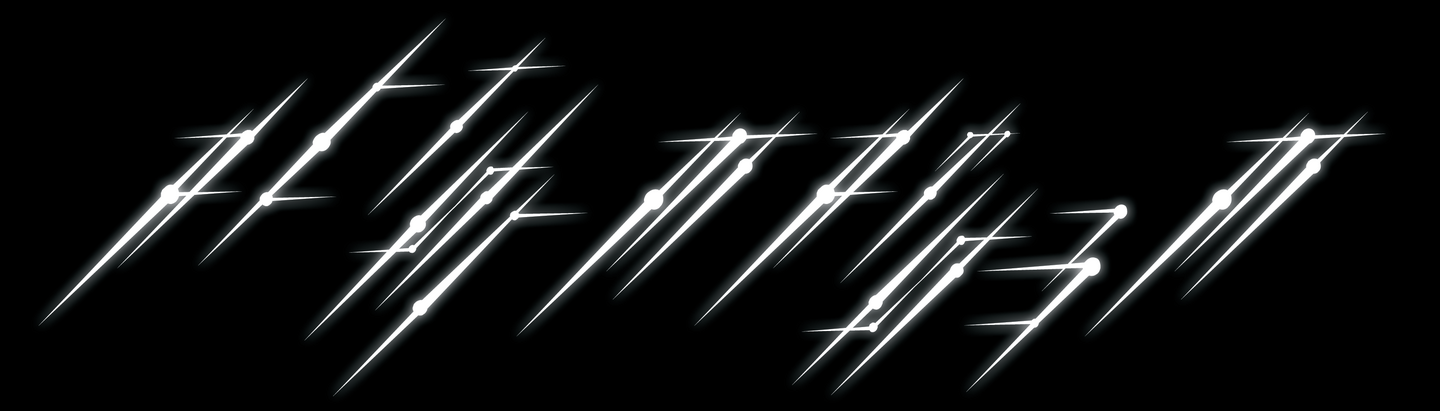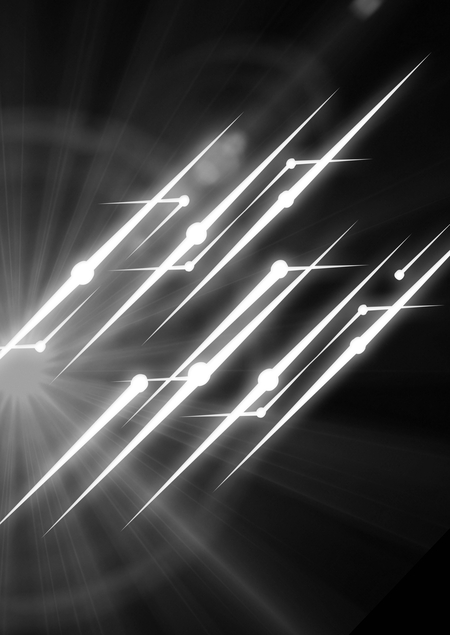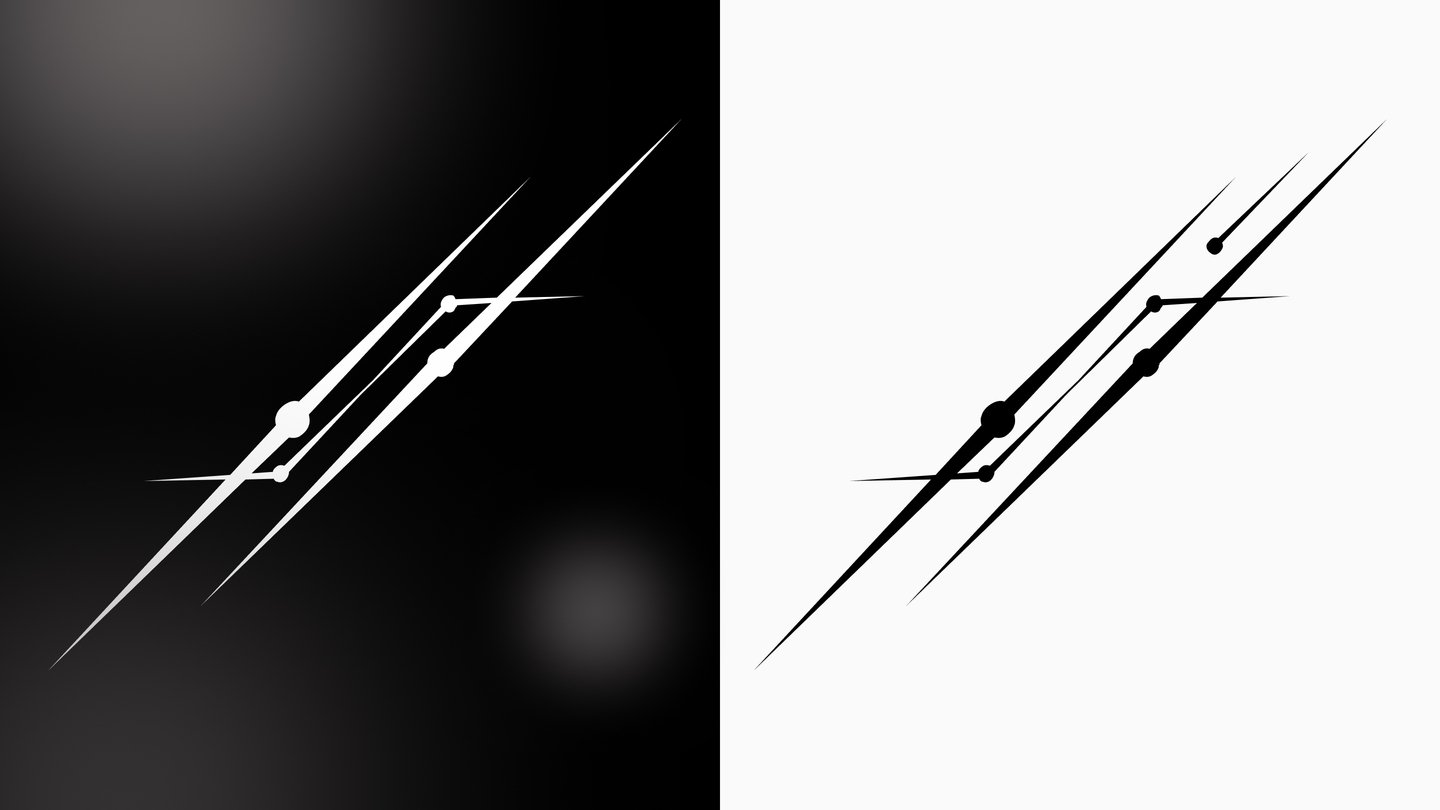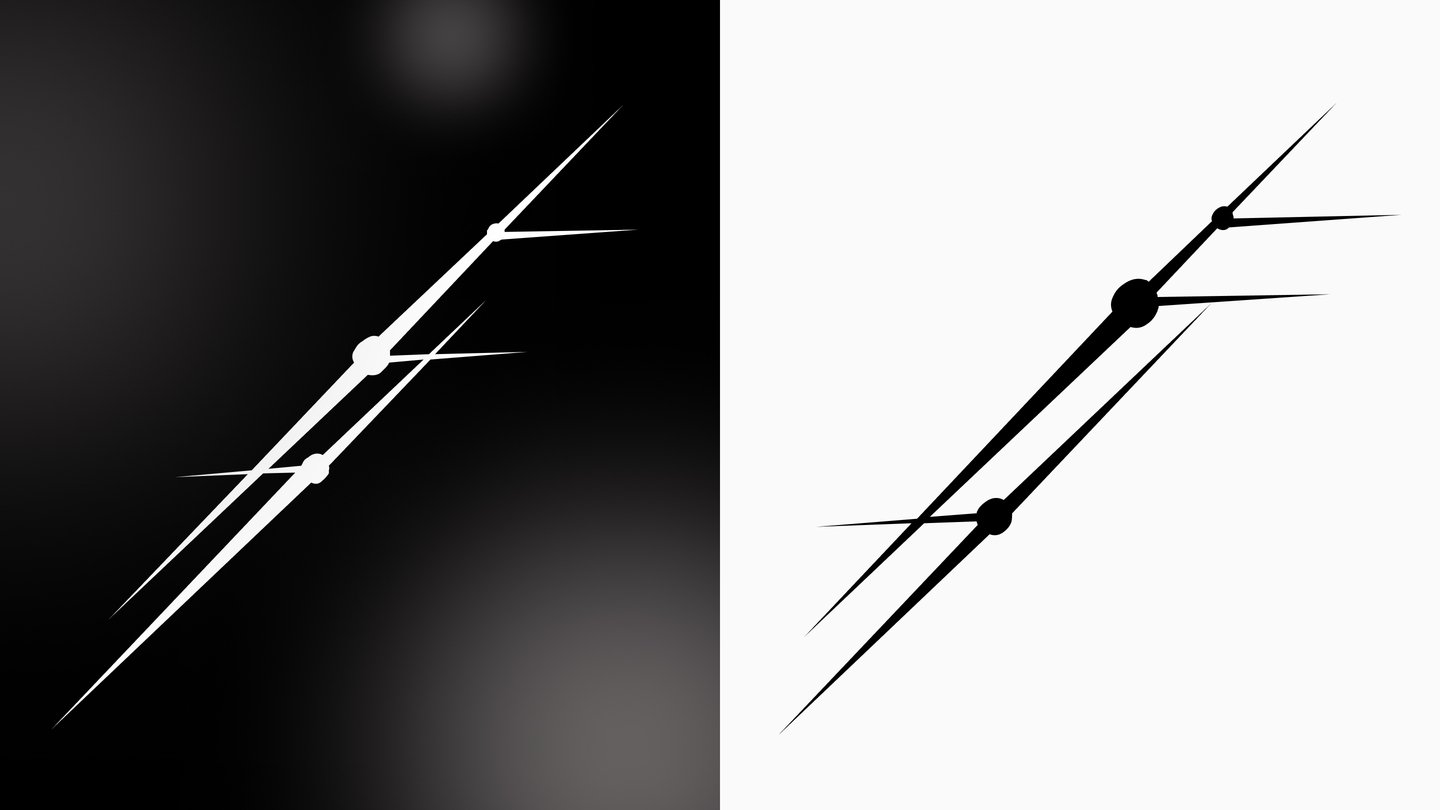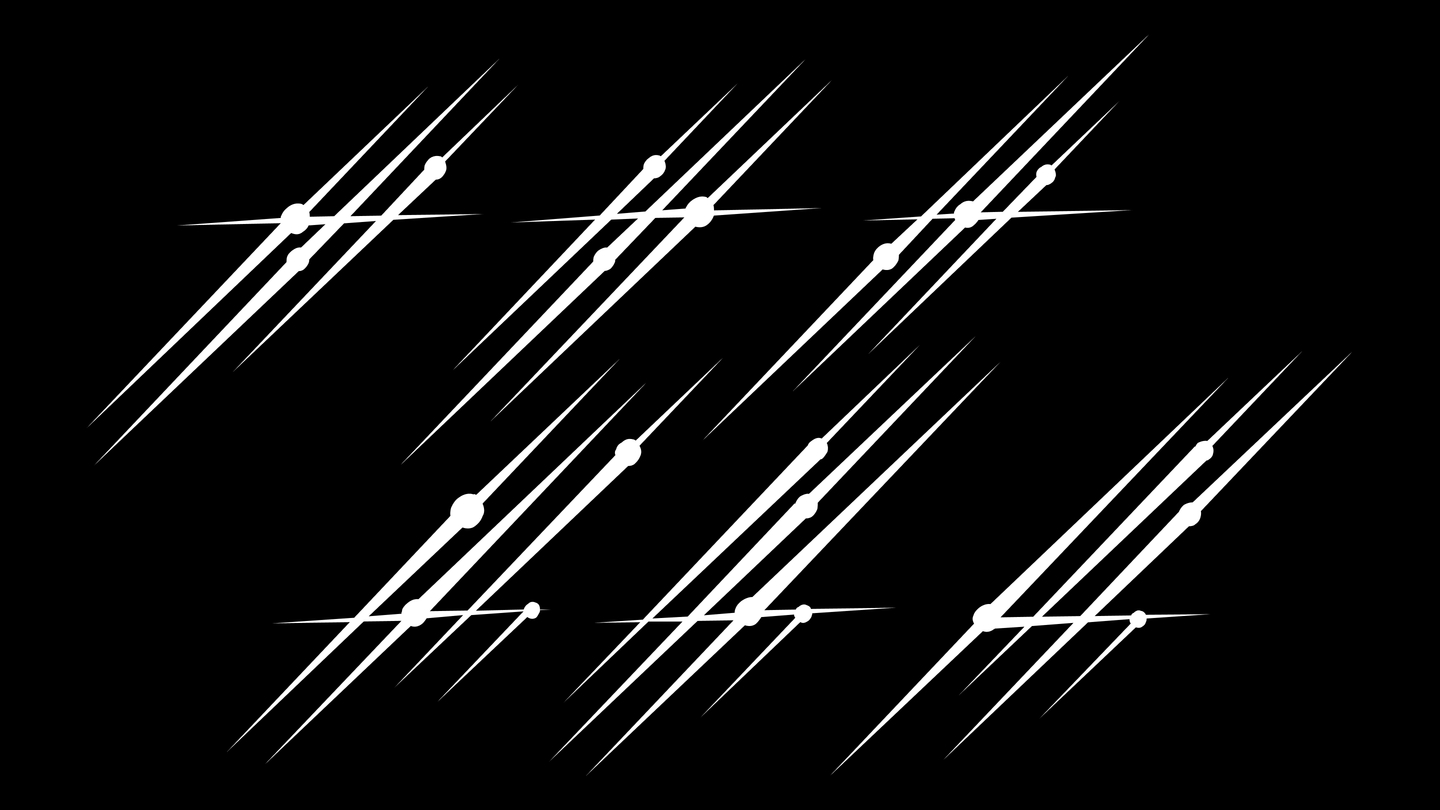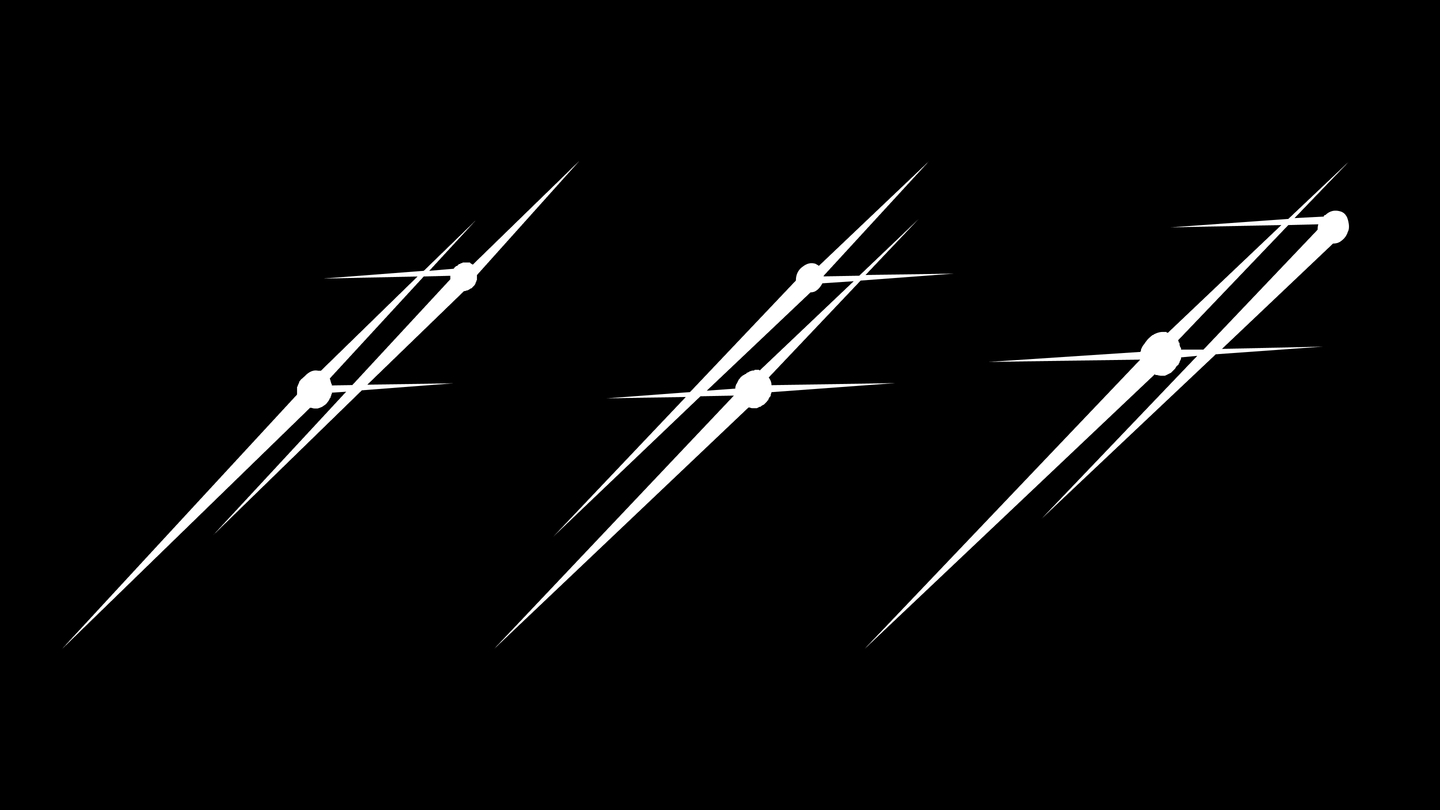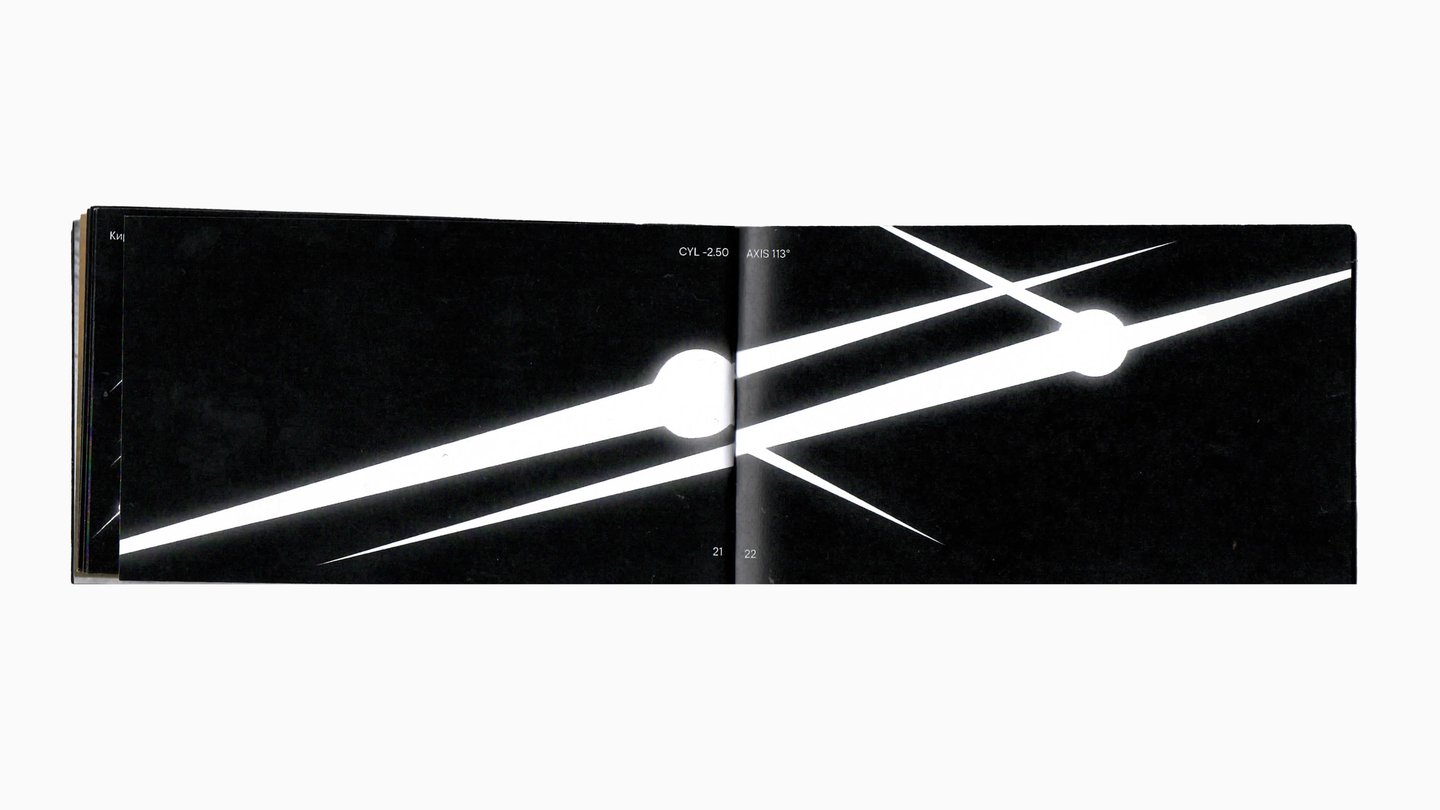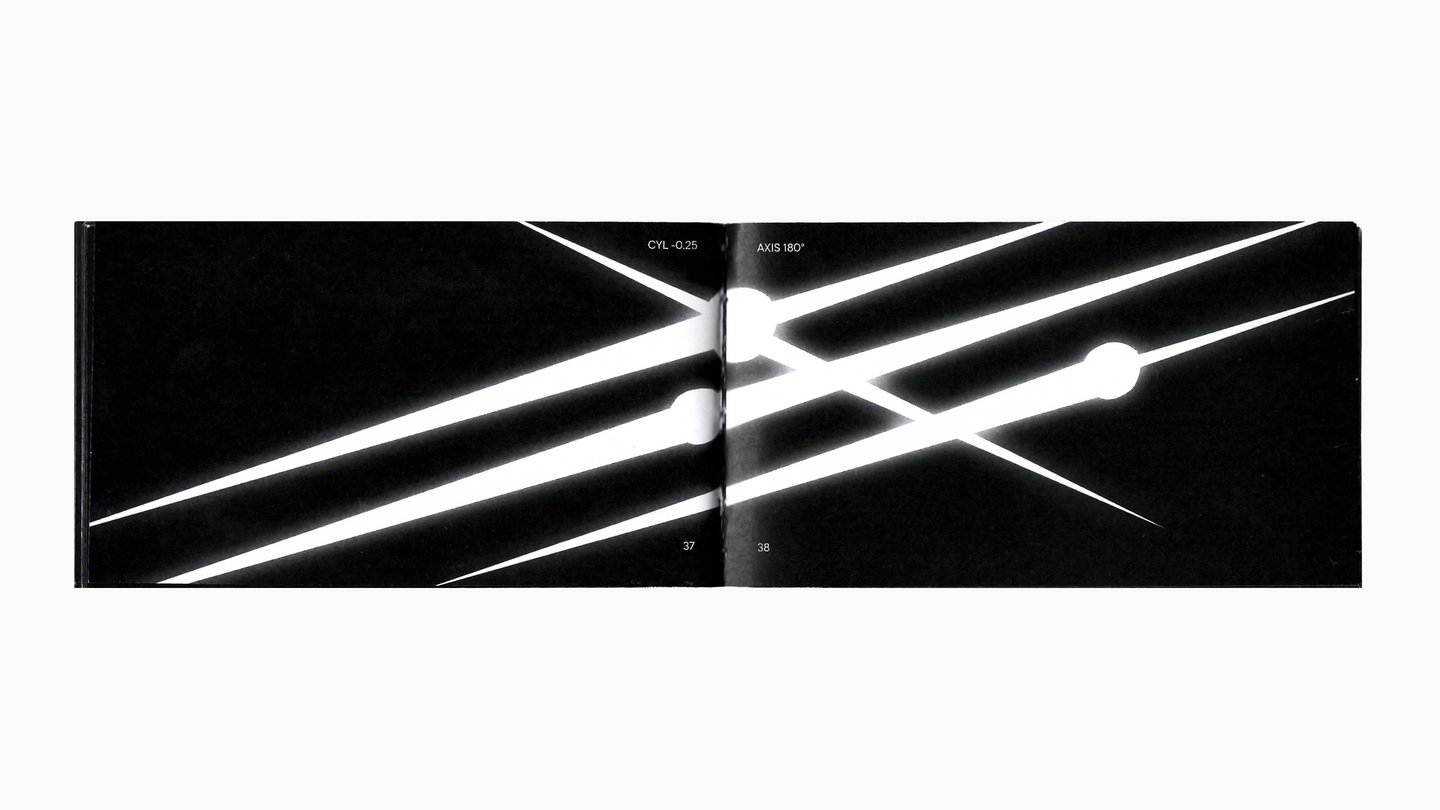
Наблюдая за городом, я заметила, что свет всегда выглядит для меня особенным образом. Уличные фонари, фары автомобилей и светящиеся вывески превращаются в лучи и звёздчатые формы. Этот визуальный эффект, вызванный астигматизмом, стал отправной точкой и главным источником вдохновения для создания шрифта.
*Астигматизм
Астигматизм — это нарушение зрения, связанное с неправильной формой роговицы или хрусталика глаза. Из-за этого свет преломляется неравномерно и не может сфокусироваться в одной точке на сетчатке.
В результате изображение воспринимается размытым на любом расстоянии, а яркие источники света могут выглядеть как лучи, блики или ореолы. Именно этот визуальный эффект стал основой для создания данного шрифта.
Модули, которые использовались для создания шрифта
Буквы кириллицы
*Источник света
Каждая буква имеет 2–3 начертания, отличающихся характером световых переливов. Это позволяет уйти от классической статичности шрифта и придать ему больше визуальной выразительности.
Альтернативные глифы
*Свет становится формой
Буквы латиницы
Знаки и символы шрифта
*Искажение